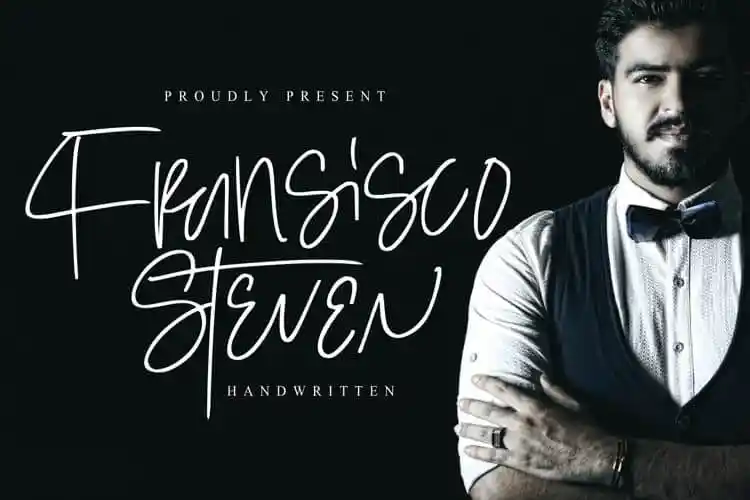
Steven Fransisco Handwritten Font – Download Grátis
A “Steven Francisco Handwritten Font” é uma escolha ótima para quem busca adicionar um toque autêntico e elegante a suas criações digitais. Criação do designer Goodigital13, esta tipografia script apresenta um estilo natural que se destaca em qualquer layout. Com letras maiúsculas e minúsculas presentes, alternativas para as letras minúsculas, suporte multilíngue, números e pontuação, a fonte “Styled Bright” deixa seus projetos convidativos e sofisticados. Seja você um designer gráfico ou um criador de conteúdo digital, esta fonte é uma ótima escolha para dar vida e personalidade à sua arte digital.